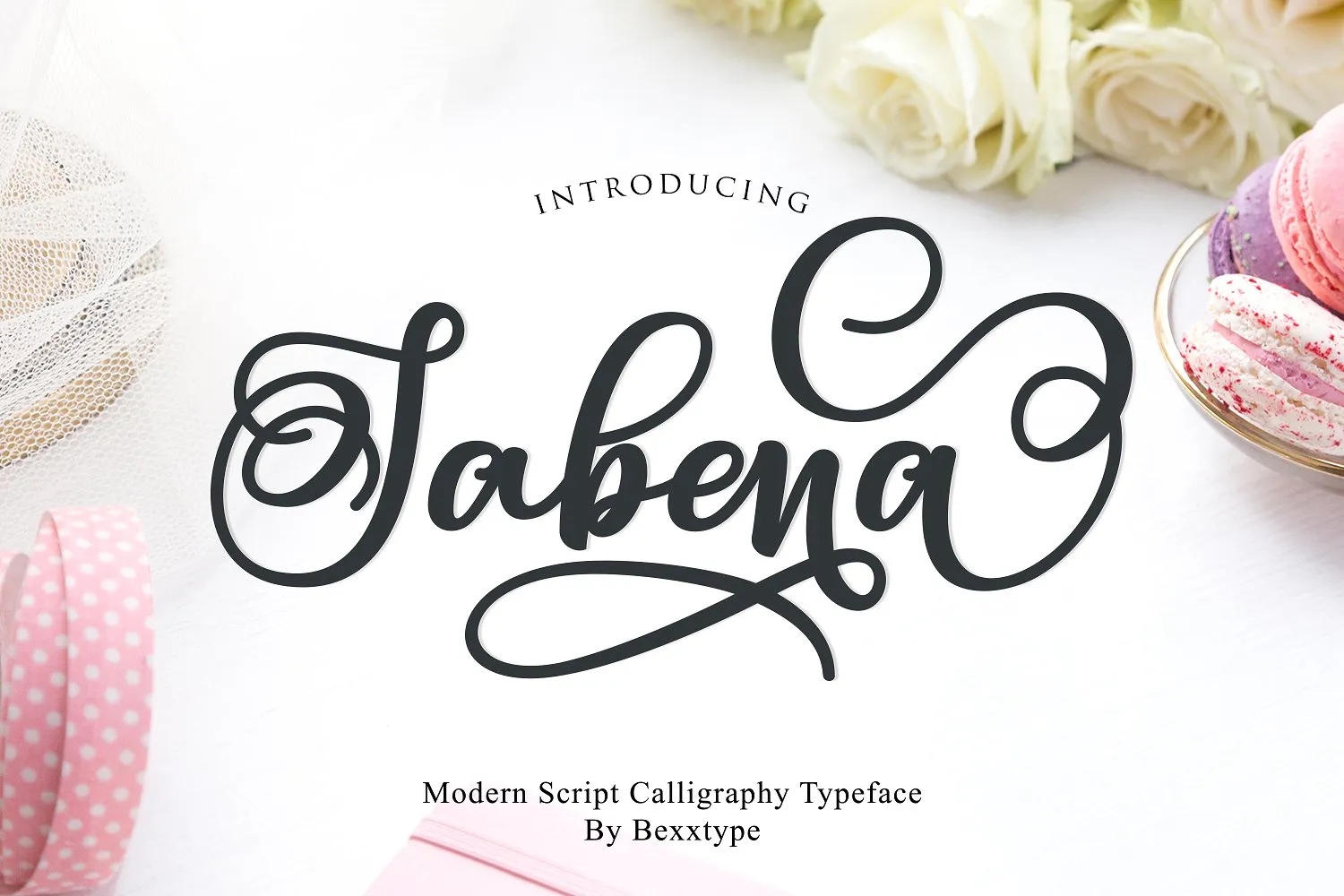
Sabena Calligraphy Font – Download Grátis
Esta é uma nova tipografia script de calligrafia moderna criada por Bexxtype. A Sabena Font apresenta um estilo casual chic que revigoriza qualquer projeto, especialmente em cartões de convite, cartazes, materiais de marca e aplicações pessoais. Introduzimos a Sabena Script Sweet, uma fonte script cheia de personalidade com estilos de calligrafia elaborados e linhas que dançam ao longo da página. Esta elegante e versátil fonte será o toque final perfeito para seus trabalhos, adicionando um brilho único a qualquer projeto. Seja uma carta de boas-vindas, um cartaz ou uma carteira de negócios, a Sabena Font tornará seu trabalho ainda mais especial e inovador.